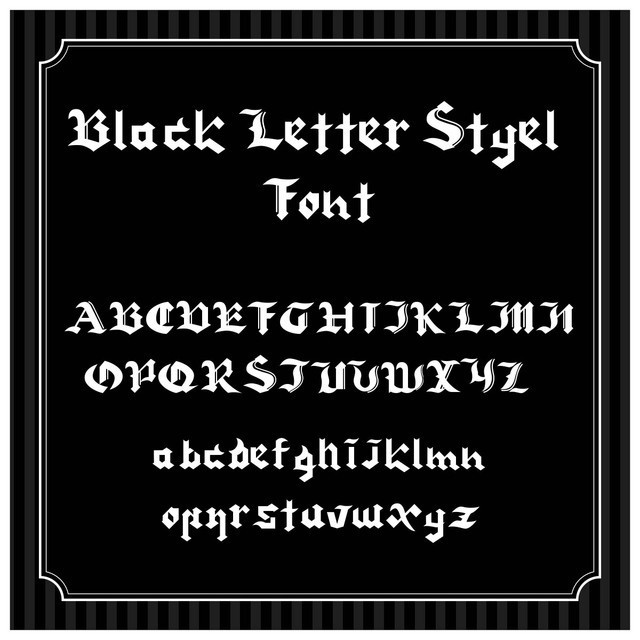
blackletterstyel_font(ブラックレター風フォント)【個人利用のみ】
このblackletterstyelフォントは213ちゃんが作った6個目フォントで 【個人利用のみ】のフリーフォント(freefont)です。 アルファベットのみなので【個人利用のみ】です。 いつかはかっこいいブラックレターにしてあげるからね!!(このフォントへの表明) 当フォントを利用した制作物などを、SNSで教えてくれると励みになります。 制作時のお気に入りポイントをnoteで記事にしています。 https://note.com/sweet_2727/n/n97c2e222cb02 ぜひ遊びにきてね!スキ!お待ちしています。 【収録内容】アルフファベット(大文字・数字のみ) 【Readme】フォントご使用上の注意 ・フォントの著作権は、213ちゃんに帰属します。 ・可愛がってくださるとうれしいです。 ・無断転載・再配布は堅くお断りいたします。 ・DLしたフォントに起因する損害は補償致しかねますので予めご了承ください。 ・使用する際の不明点はお問い合わせ先にご連絡ください。答えられる範囲でお返事いたします。